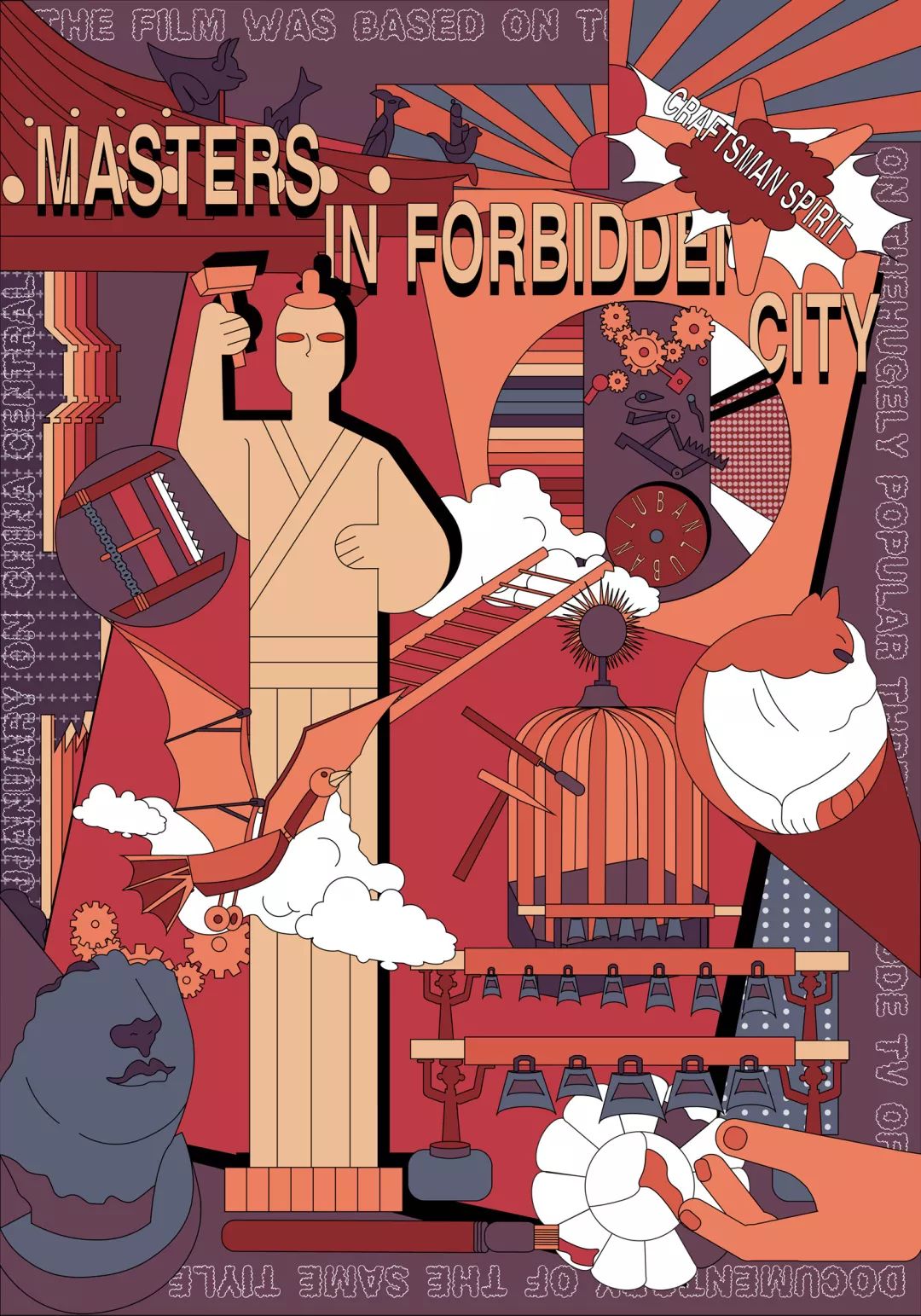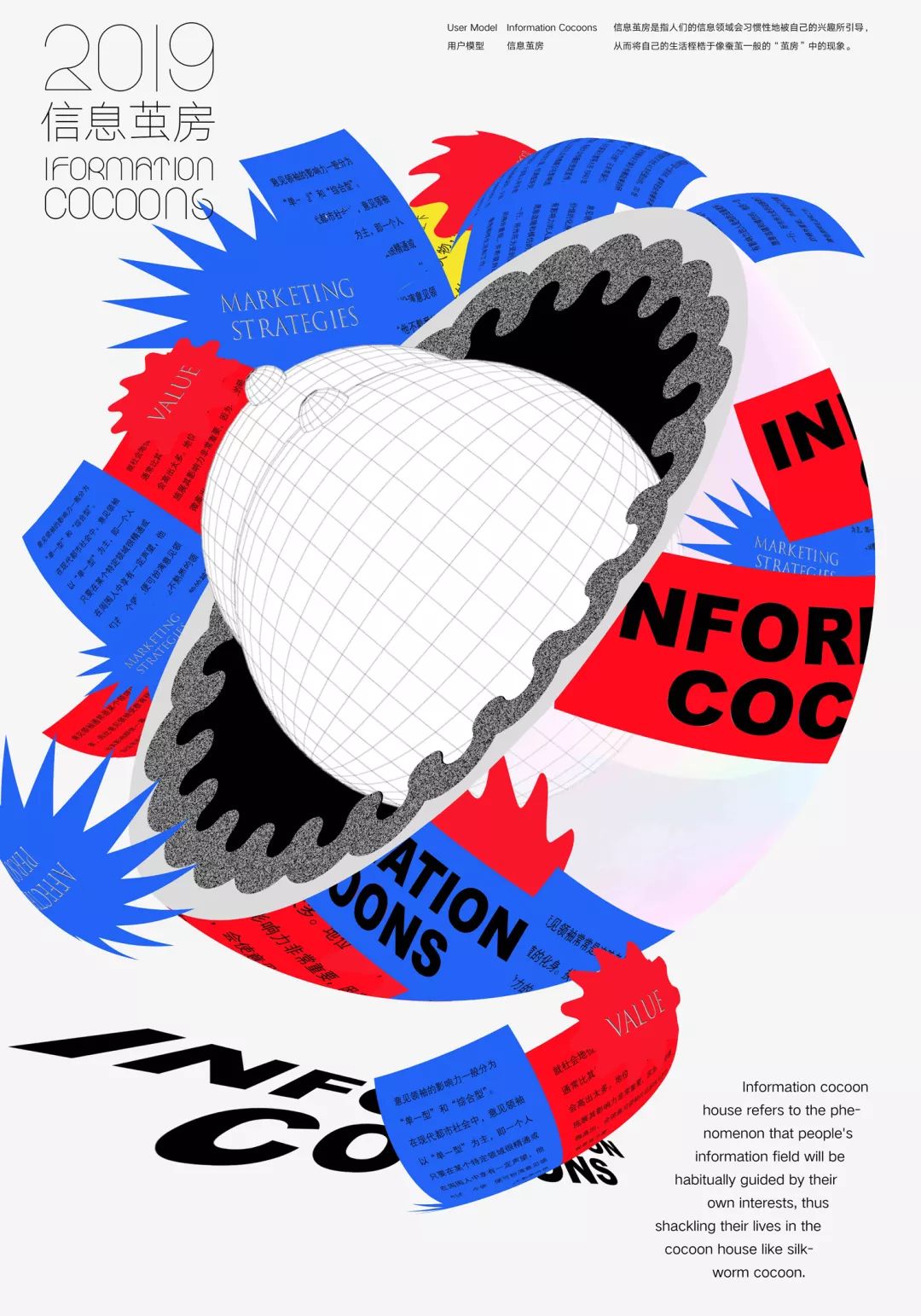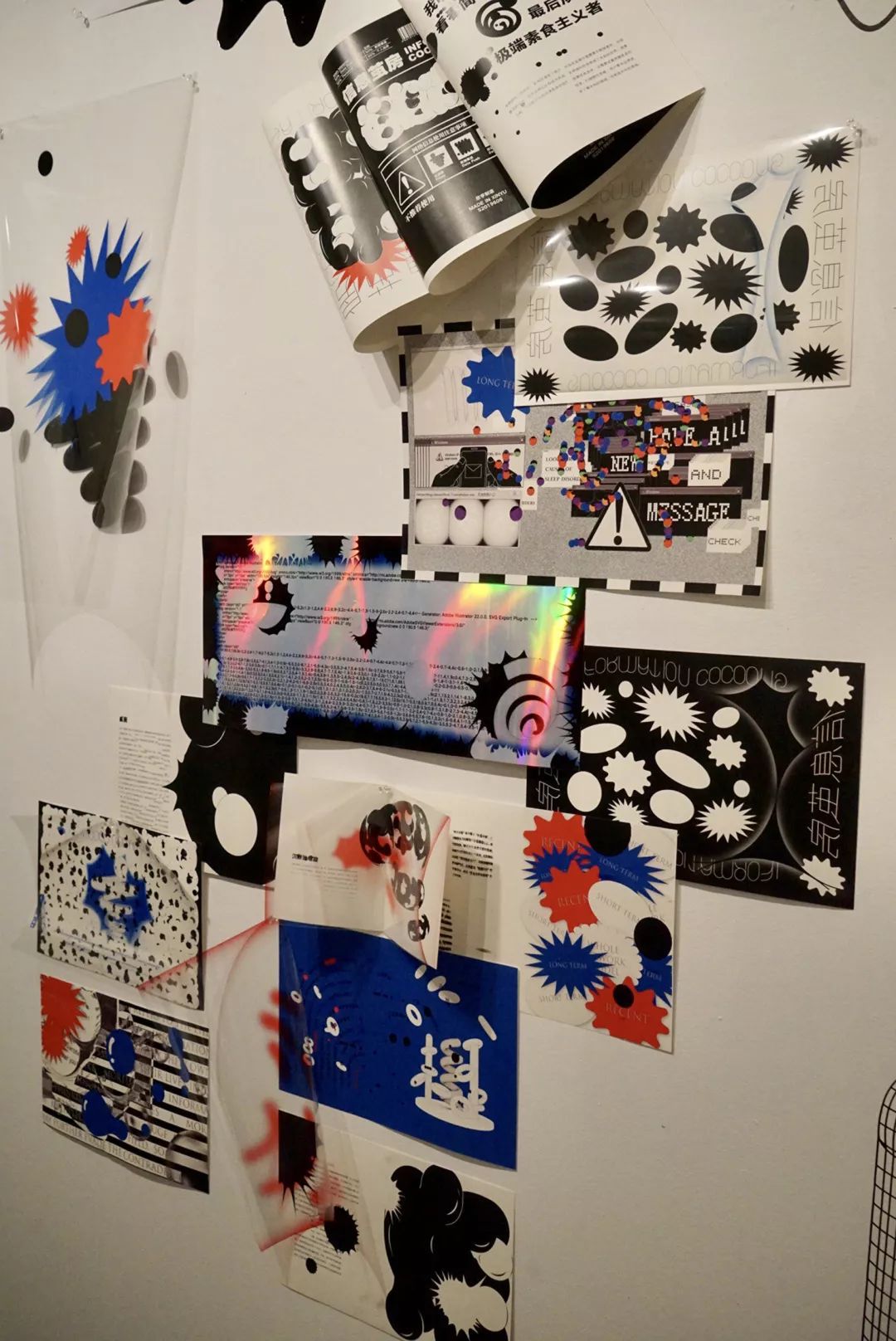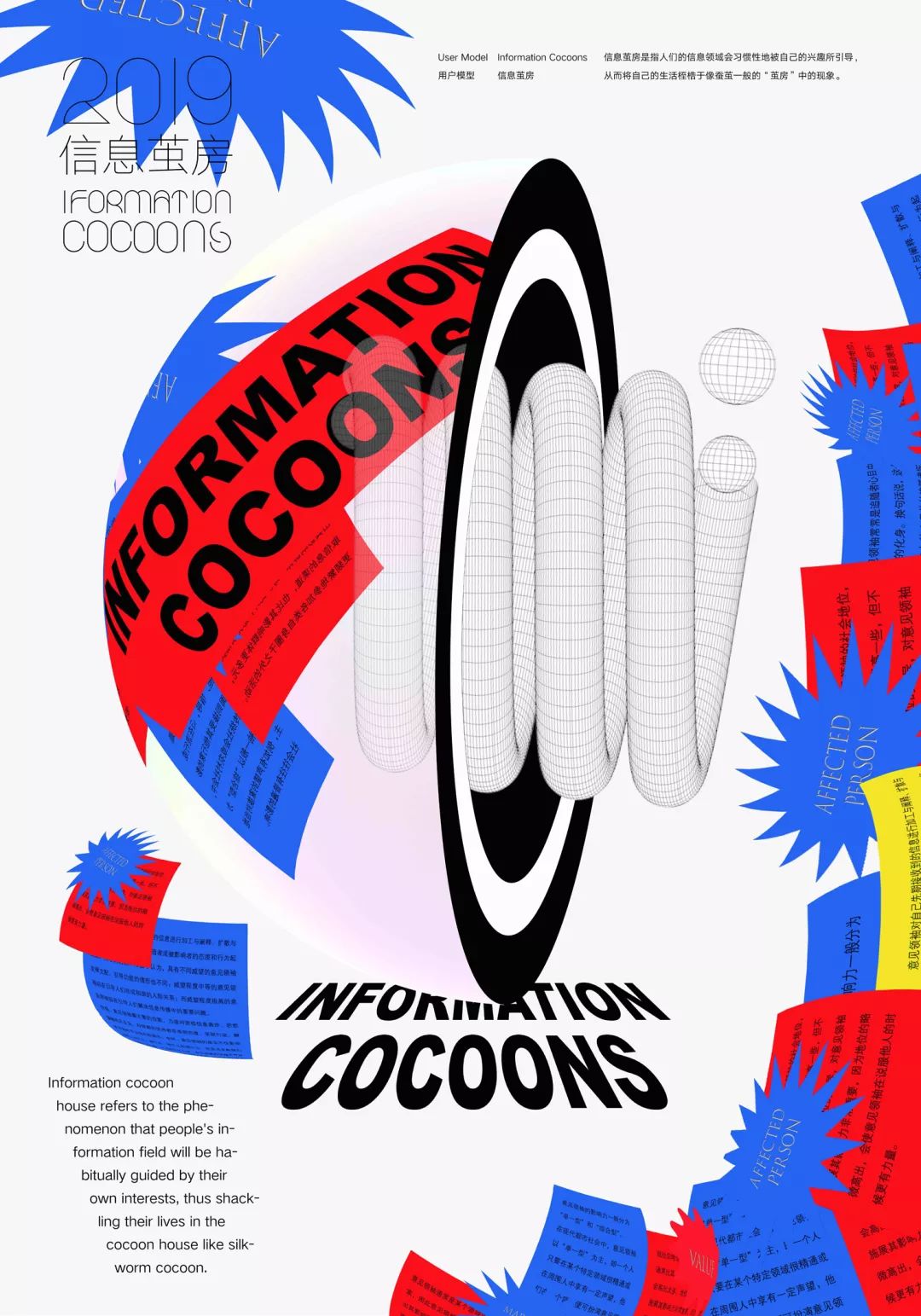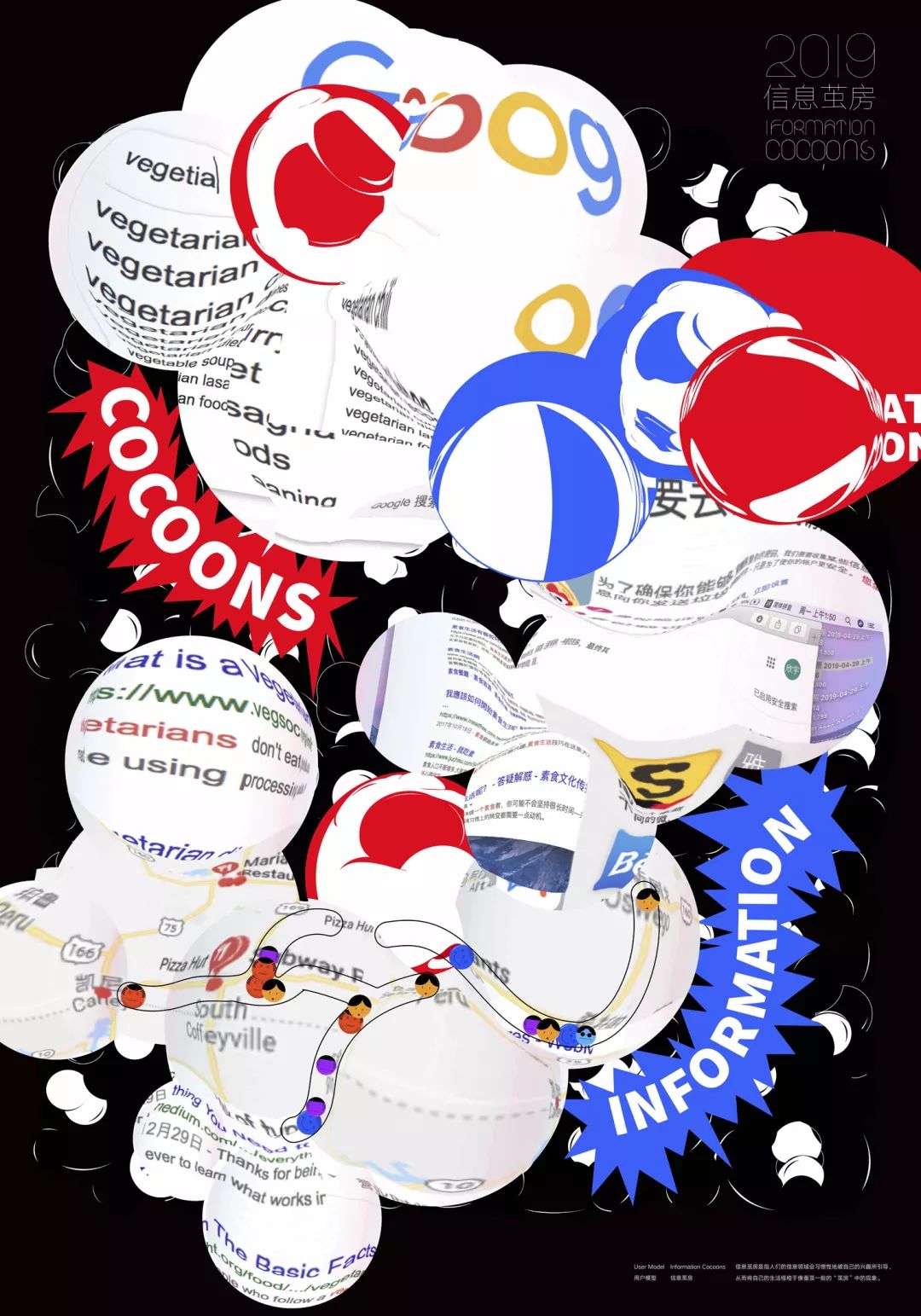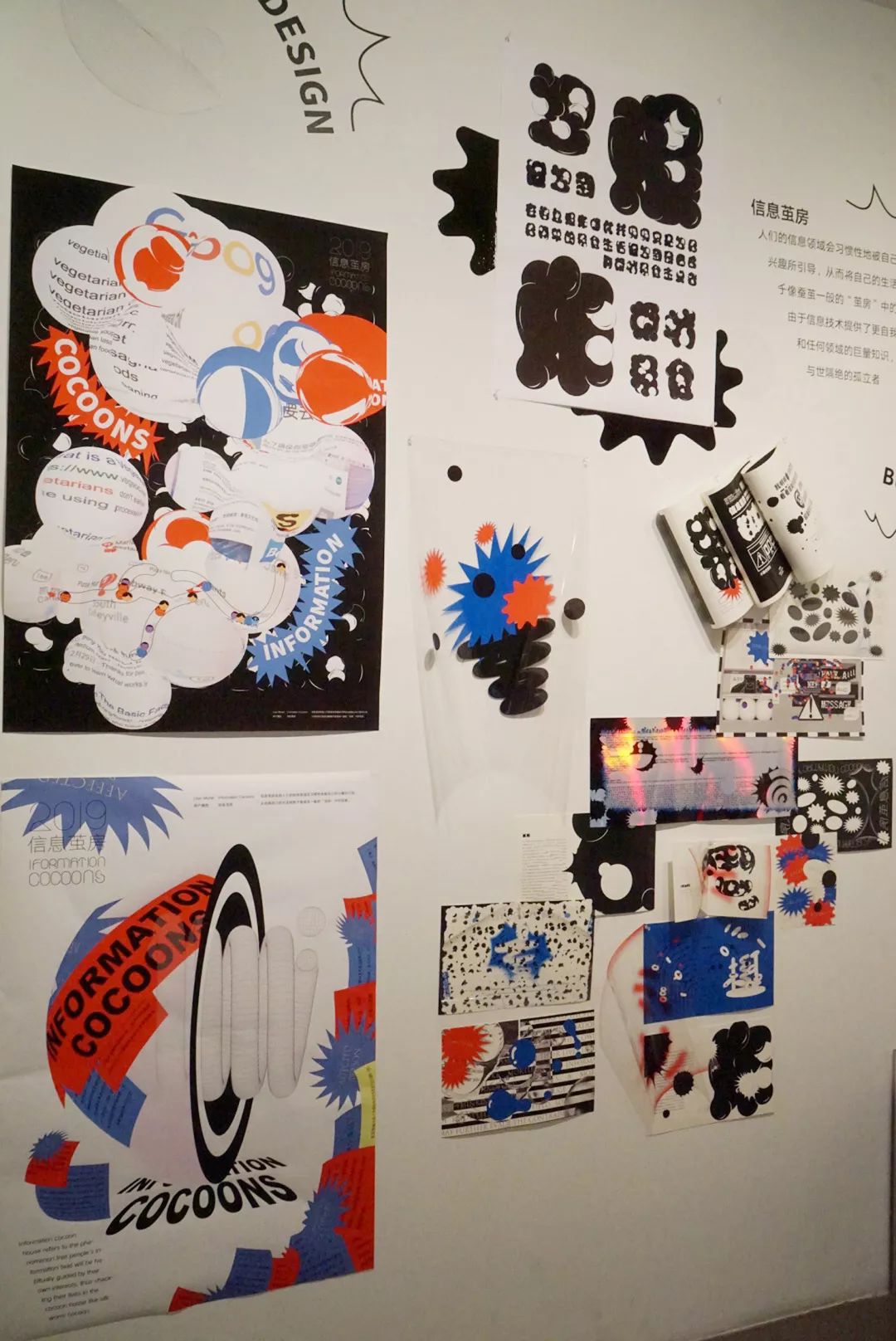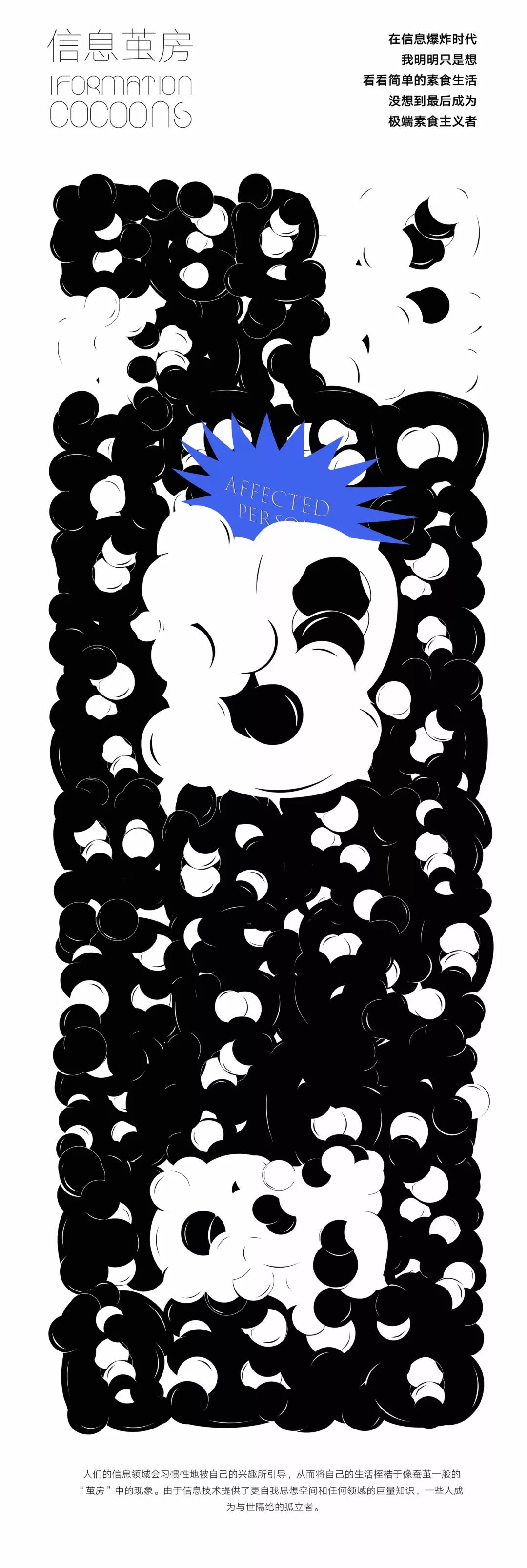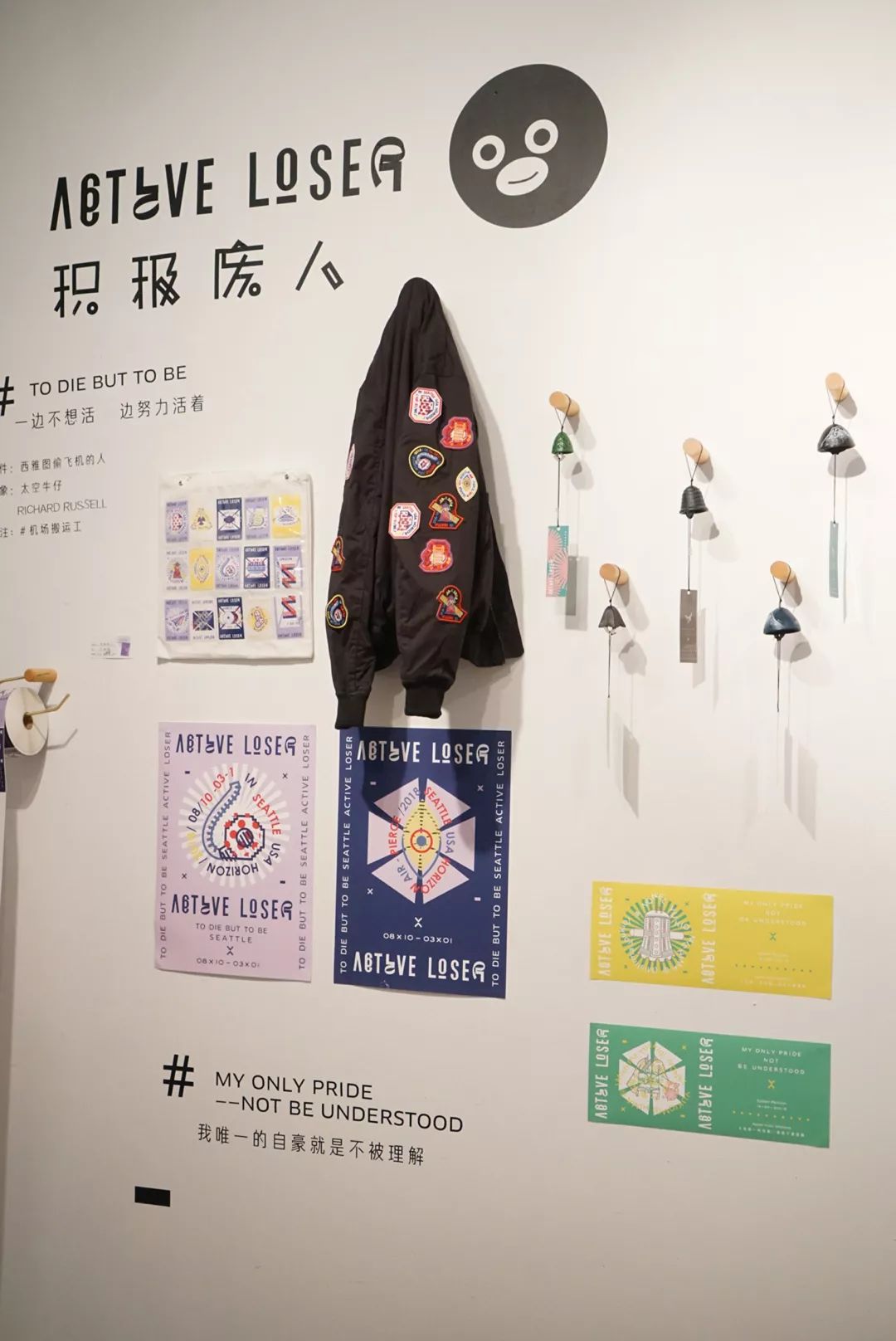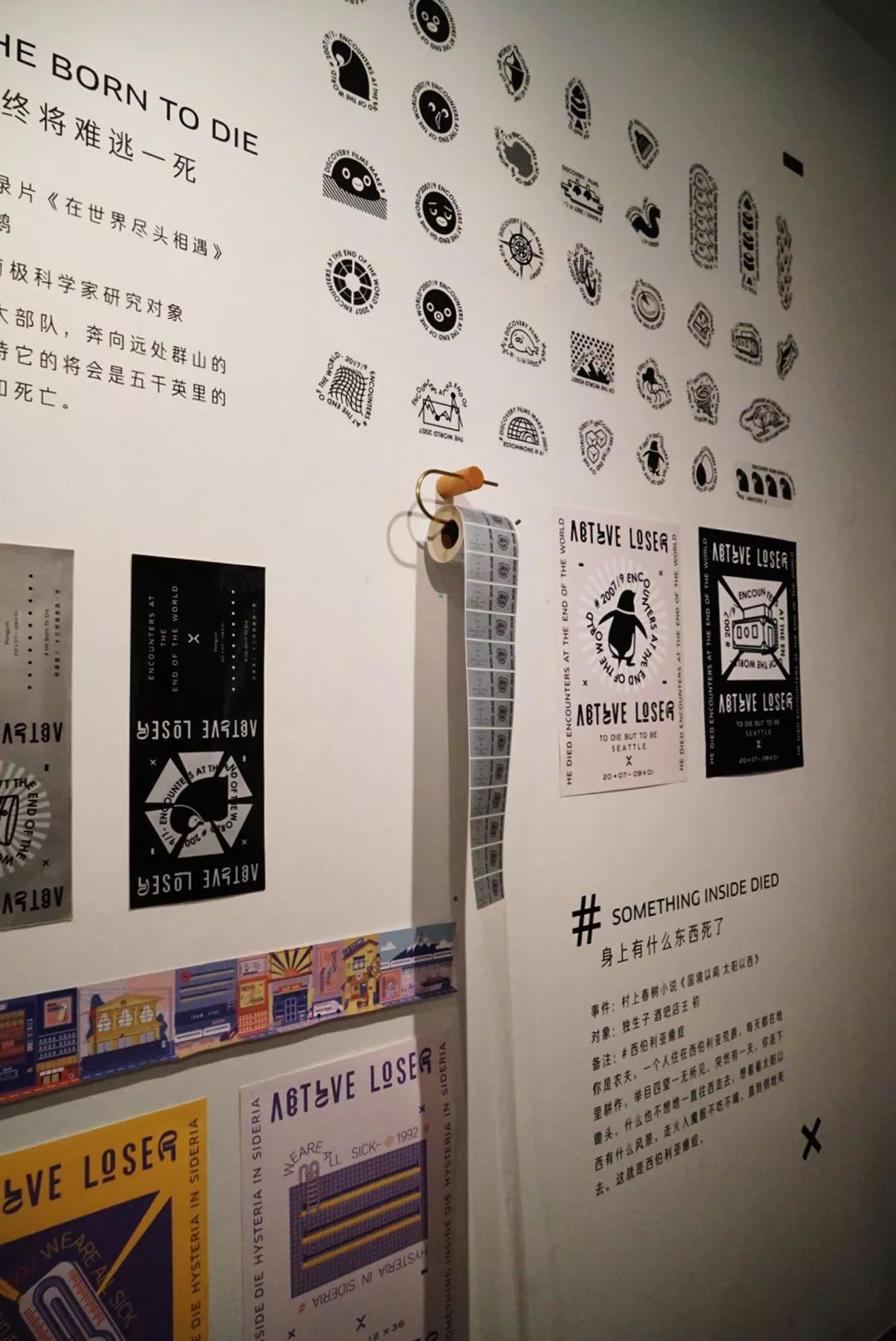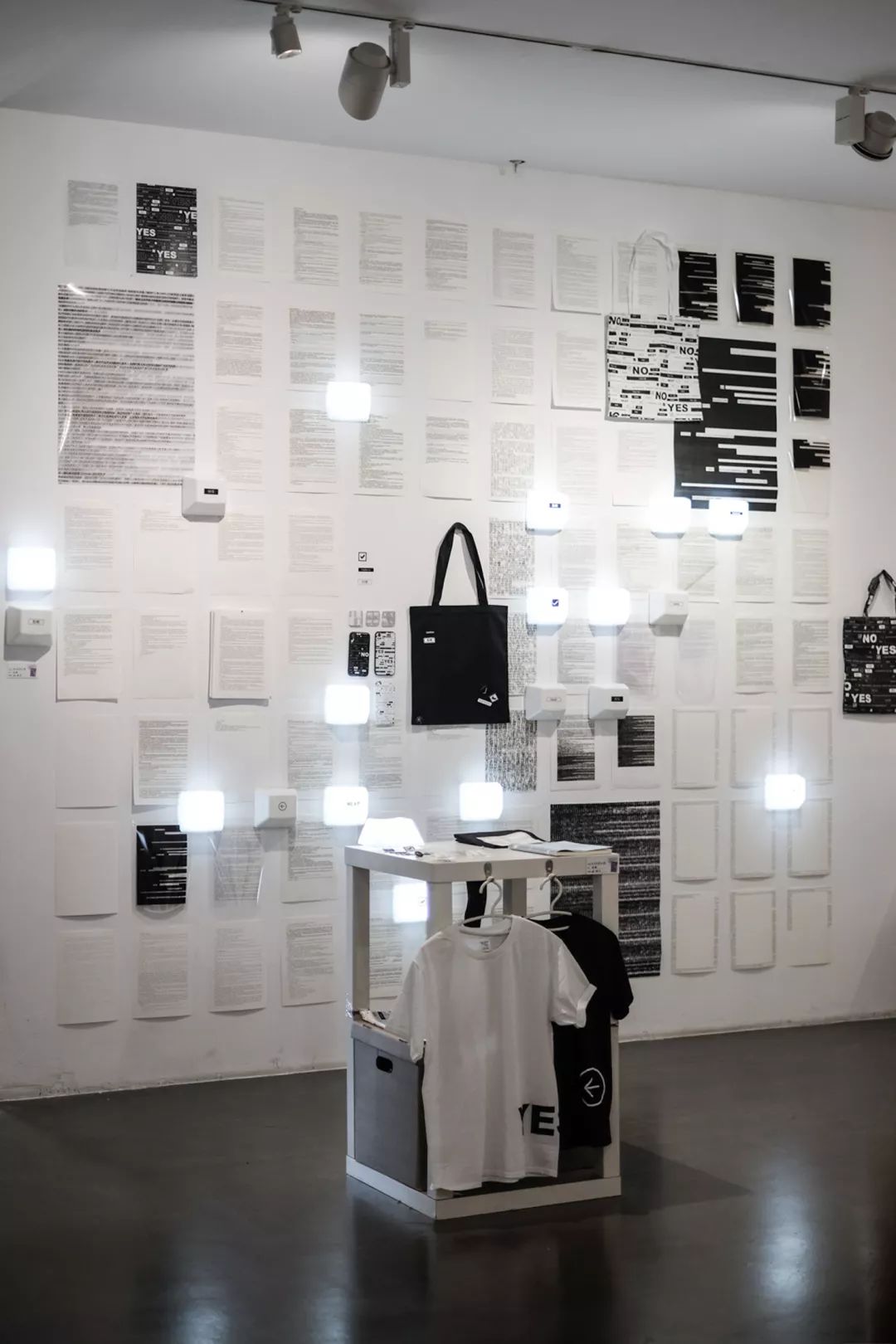
南京艺术学院2019毕业设计作品
毕业展主视觉
毕业展介紹
人之所以为人,在于“认知”:认知人的界限,认知人的价值。尔后方能开启心智,寻求意义,做出选择,构筑未来。
南京艺术学院设计学院2019毕业展主题为“实验x认知”:不断实验,丰富认知。行走与思辨之中,我们了解真实世界,触摸本体。以观念之美、形态之美、材料之美、技术之美、结构之美致敬千界万象,转译万语千言。
2019年5月20日-6月5日,6月8日-6月14日,南艺设计再次以高质量毕业作品(约750件/套)亮相于南京艺术学院美术馆、设计学院展厅、设计学院实验楼与整个校园公共空间。
与此同时,南艺设计又以“公共认知”为主线,“演绎”、“品物”、“纪念”、“日常”、“对话”为议题,在南京大报恩寺、南京德基广场、侵华日军南京大屠杀遇难同胞纪念馆、江苏电视台荔枝文创空间、美国旧金山联合广场举办5个重要平行展,向南京这座和平城市提交关于设计之公共价值的答卷。
由点及面,南艺设计继续思考设计与人、设计与物、设计与社会的关系,尊重一切人文实验。
南京艺术学院设计学院
平面设计本科作品
追星时代
毕业生: 陆晨
导师: 何方、王帆、陶霏霏
现在真人秀节目变得流行起来,拉近了明星与粉丝之间距离的一种方式,工匠大师鲁班和《我在故宫修文物》非常匹配,陶渊明如果去参加现在大热的综艺《向往的生活》会是什么样的景象?将选择的历史人物与综艺节目有机结合,能够产生很多新的想法。
信息茧房
毕业生: 陈欣宇
导师: 何方、王帆、陶霏霏
过于强大的信息技术和习惯性地搜索自己感兴趣的东西,让人们可以有意无意地禁锢在自己的天地中,脱离网络社会中的种种矛盾,从而产生各种负面影响,一方面希望通过对信息茧房的数字图像化语言的阐释,引起一定的社会关注,使更多的公众认识到这种效应的危机,另一方面网络行为是一种抽象的概念,网络信息的运作则是理性复杂的,但有程序语言的规律可循,作者希望通过对数字图像化语言的实验性探索,结合3D等技术用一种程式化、符号化的设计语言去阐释茧房效应,并在视觉上带来理性的美感。
《共生体》
毕业生: 陈衍
导师: 何方、王帆、陶霏霏
由对时下热门社会问题的关注引起的对现代社交环境下人与人之间交往关系的形成以及对形成的共生关系形态的思考。共生它指的是一种来源于生物学上的,广泛的共生,而最常提起的互利共生只不过是共生关系中的形态之一,而生物之间的共生关系与人与人之间的共生关系具有很大的相似性。所以我希望将目光聚集到人自我本身,探索当代社会环境下人与人之间的交往关系,通过将生物的六种共生概念融入到人类社会交往中,创造出三十六种共生图形,用一种浅显的、抽象的视觉呈现方式来表达复杂的共生概念,同时让观者更多的关注到对社会共生关系的探讨这一议题。
《人造景观》
毕业生: 陈伊婷
导师: 何方、王帆、陶霏霏
后工业时代带来文明社会的繁荣,但在这激荡的表象下,却是肆意改变自然形态;大量人造物的废弃,程度及数目之大所造就一切物体的聚集形态,令人震撼;工业生产与城市建设对自然的强势入侵,留下了不可磨灭的痕迹。眼前这个世界的自然景观正在以某种姿态提前逝去,取而代之的是大量从未有过的“人造景观”的涌现。笔者结合数码图像技术与“超现实手法”的运用,构建出一个全新视觉的“人造景观”。
积极废人
毕业生: 何秋瑶
导师: 何方、王帆、陶霏霏
“积极废人”的灵感来源于现代生活中那些看起来积极向上其实内心颓废的人群。以四个主题表现:新闻《偷飞机的年轻人》中“一边不想活,一边努力活着”的美国年轻人,纪录片《在世界尽头相遇》中“它终将难逃一死”的企鹅,三岛纪由夫《金阁寺》中“我唯一的自豪就是不被理解”的年轻僧人,以及村上春树《国境以南太阳以西》中“身上有什么东西死了”的男人。设计以小图标表现故事情节的方式为主,辅助以海报,文创,作为最后展品,形成一个整体的设计构成。
《生活哲学》海报设计书籍设计
毕业生: 李韶雯
导师: 何方、王帆、陶霏霏
通过梳理和设计用故事化的语言来表达十个生活哲学故事,让人们借助图形直观容易的了解运用这些生活哲学。
FUTURE BASS 节奏与音频可视
毕业生: 王逸然
导师: 何方、王帆、陶霏霏
我们在生活中是随时都在和音乐交谈的。我选择FUTURE BASS 作为主题是因为在这类音乐中,有着多样化的低音贝斯,也有着其他许多还未探知的元素。在两张主海报中,我主要突出了未来贝斯中的四个元素-低音贝斯,波形,鼓点节奏和和弦。在这四个主视觉中,我主要研究了低音贝斯和波形的视觉语言,图形的组成有随机性,也有人为的控制。作品中图形等生成主要朝着未来,新颖,独特的方向前进,不拘泥于传统图形图像等。作品基于点,线,面,给大众呈现三者的结合和运用,也给大众传递了关于FUTURE BASS-未来贝斯领域的视觉语言。
《我已阅读并同意》
毕业生: 胡瑶
导师: 姚翔宇
大部分用户在使用软件时,对其提供的最终用户许可协议,直接点下已阅并同意的按键,但并不真正进行阅读。作品试图通过分析这些文本冗长而无趣的阅读体验,研究其蒙蔽特征与可读方式。
BOXXX.LAB
毕业生: 吴采恩
导师: 姚翔宇
人们感知的主要方式是通过触觉、味觉、嗅觉、听觉和视觉。而儿童正处于成长阶段各项感官尚在发育,他们的感知可以说是探知,通过他们感知的过程逐渐认知这个世界。让他们自己自由的感知这个世界,对这个世界认知,最重要的是让他们用自己的思维来看世界,而不是把我们惯常的思维灌输给他们。
BOXXX.LAB是一个儿童感知认知体验的设计,让他们在体验中感知,在感知中认知。以盒子的形式也是为了体现出他们在自己的小世界里不被外界所干预自由自在的感知。
古字新做——以汉字“車”为例
毕业生: 李威
导师: 张抒
车
陆地上有轮子的运输工具,
声如居,
言行所以居人也。
在甲骨文中,
车有多种写法,
像车形。
许慎《说文解字》云:
横视之肖,
或云车少昊时驾牛,
奚仲始驾马。
车子
指陆地上有轮子的交通工具,
比如,火车、汽车等。
也可以指机器上等交往部分,
比如,车床等。
当然,
车,
也是一个姓氏。
以汉字的车作为设计的本源,
取其象形之态,
用平面设计的手法,
在凸显汉字本意的同时
也增加些意匠的趣味性
正是本书的亮点。
实验性甲骨文字
毕业生: 洪良奋
导师: 曹方
通过课题文字实验性设计——“感”与“度”的运用中,“感”的媒介、材质的应用将文字以不同的形式去呈现出来。“度”的数值、尺度调试后产生一系列不同类别的字符,其目的是创新甲骨文字与现代手法相结合,且最大化地传播文字的魅力。
实验性甲骨文字书籍记录每一次文字通过“度”的运算所表现出的不一样的字符,文甲骨文字八音盒以古文字笔画结构转化成音符的形式呈现美妙音乐,香薰灯发出微微清香和从文字中透出的光斑令人喜爱,以及明信片、笔记本、手提袋都是很好的去传播甲骨文字魅力的方式。